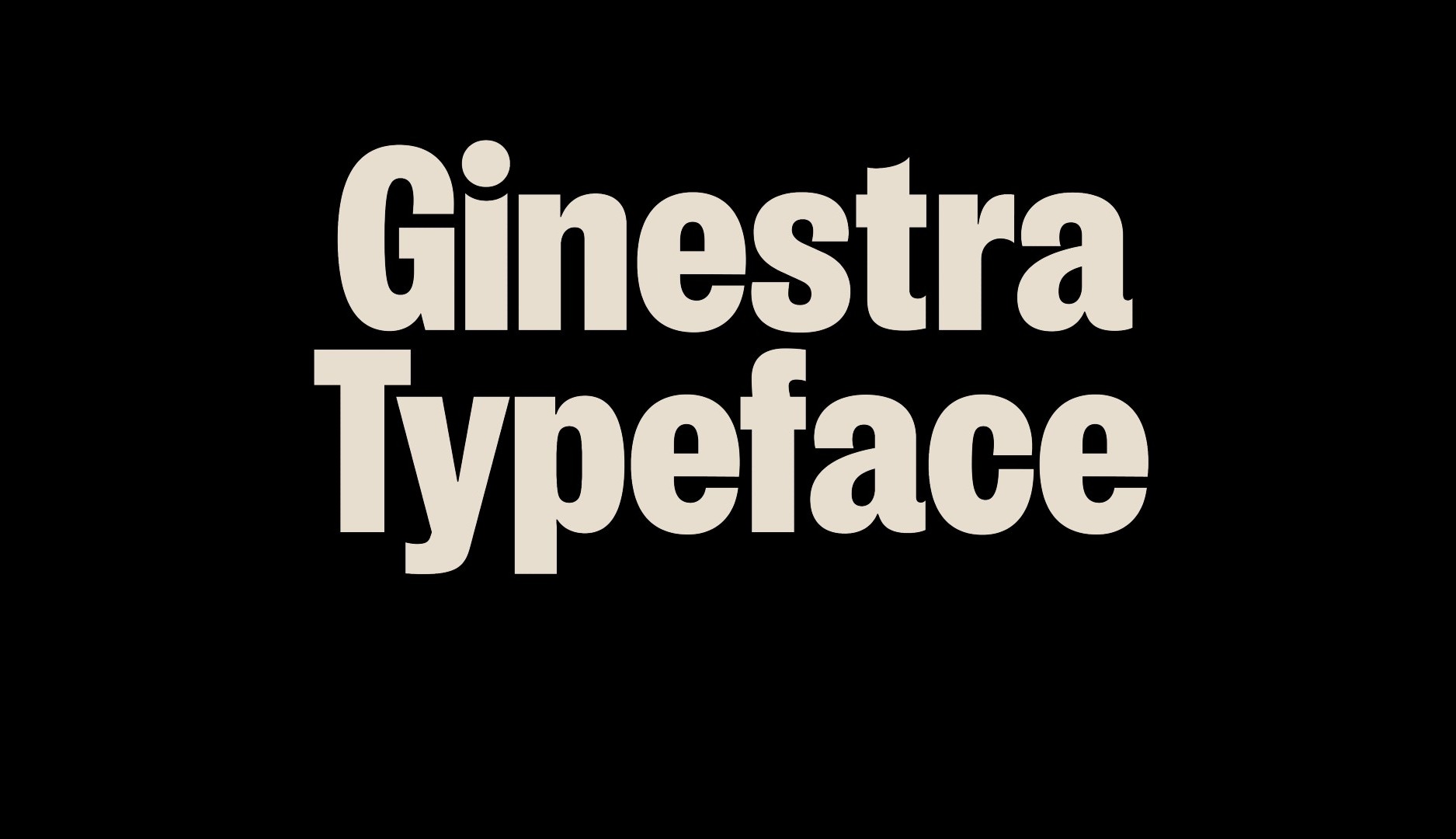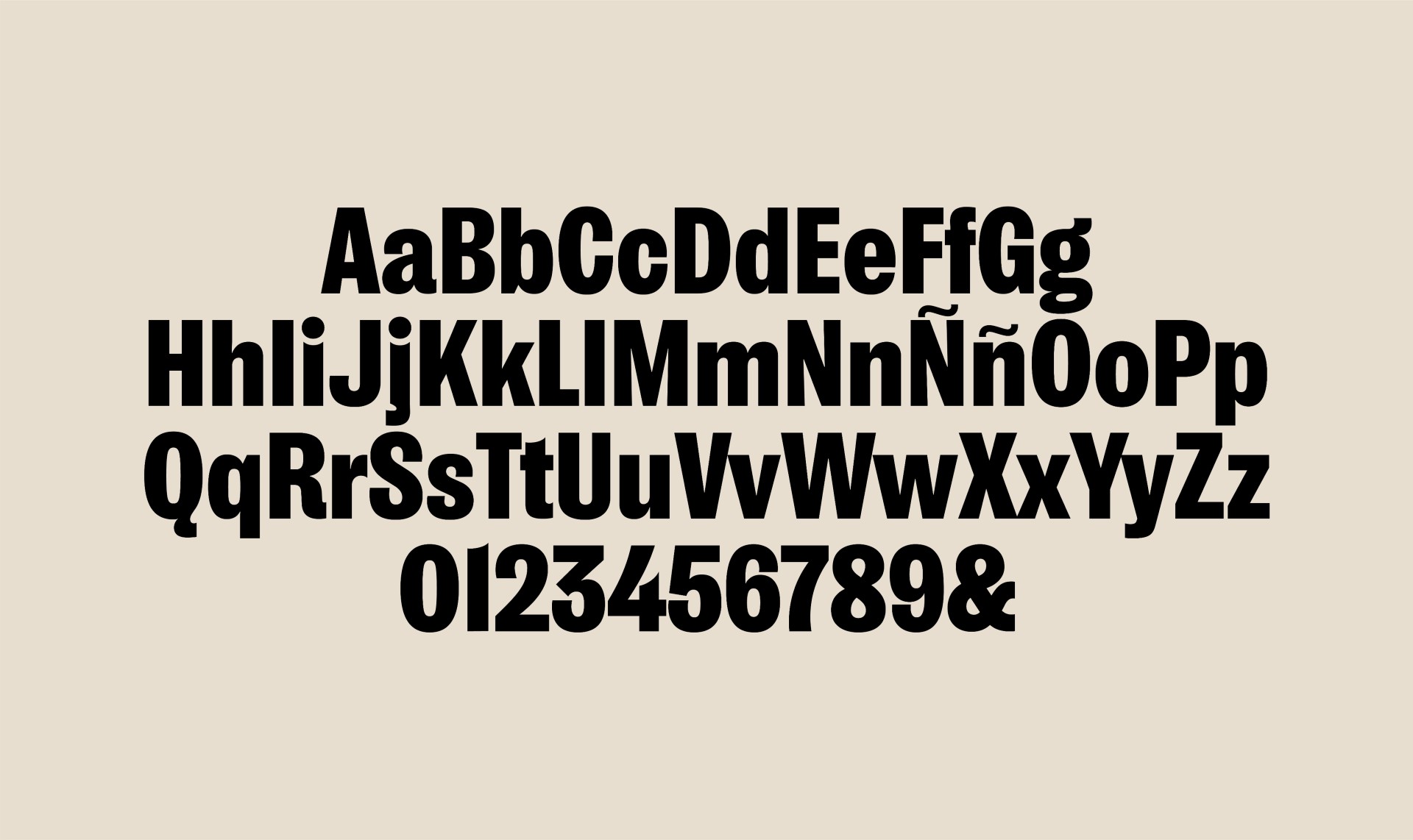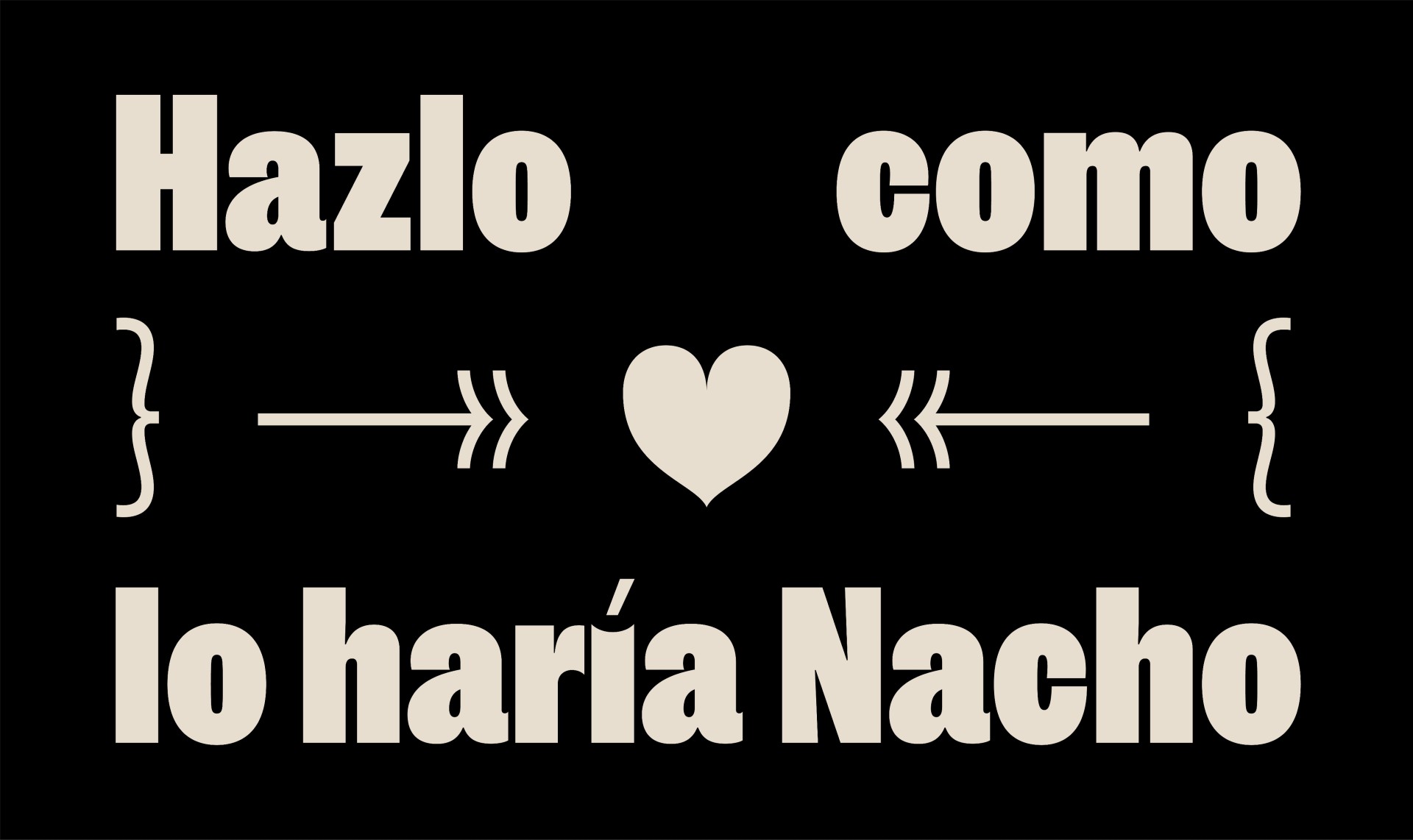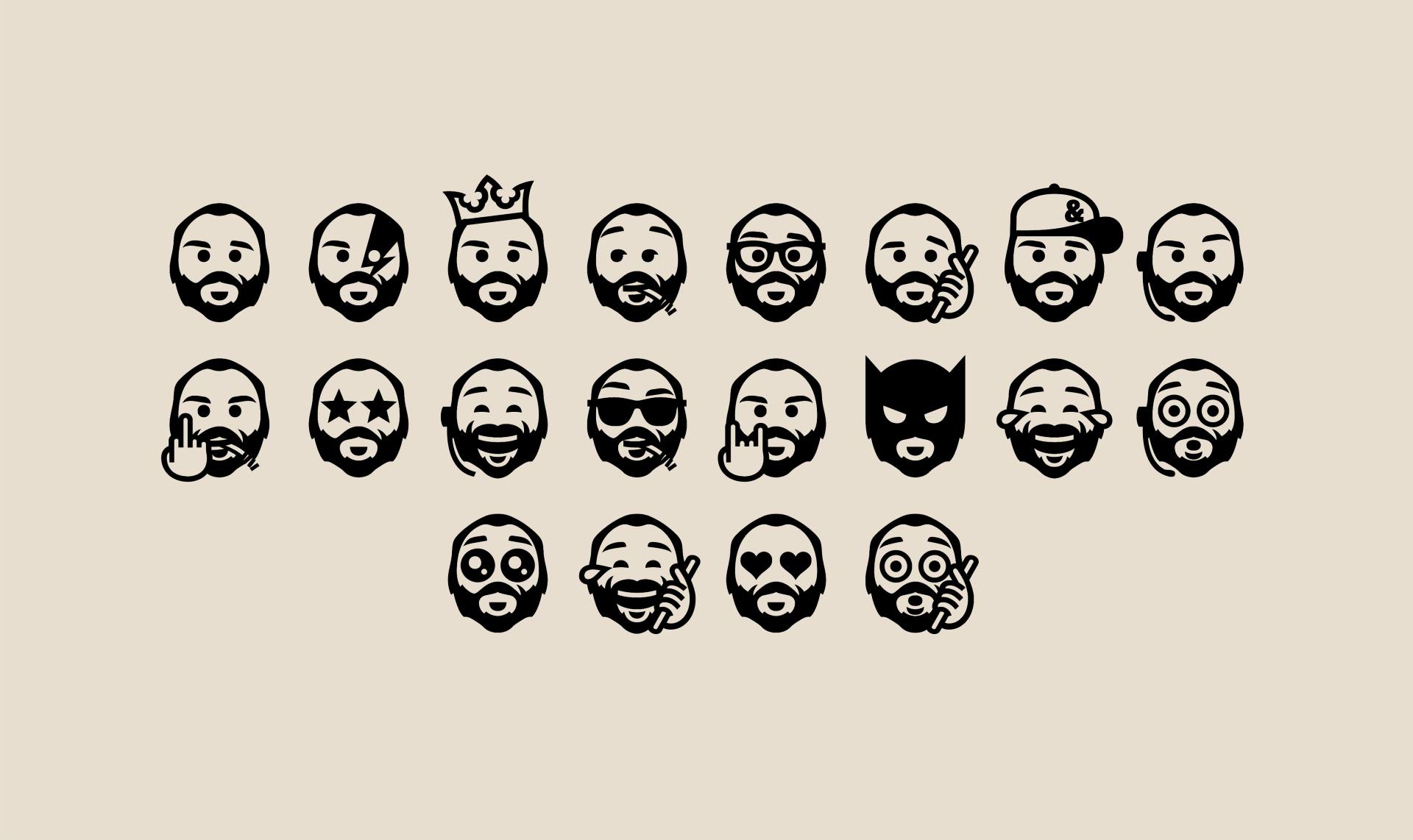
Tipografía “Ginestra”: la agencia &Rosás rinde homenaje al Director Creativo
• La agencia ha creado una tipografía inspirada en el creativo y tipografías propias del cartelismo
• Se ha diseñado en colaboración con Íñigo Jerez, Socio Fundador y Director Creativo de Extra Estudio
Tipografía Ginestra
Hace justo un año falleció Nacho Ginestra, quien fuera Director Creativo en &Rosàs, a consecuencia de una enfermedad. Con motivo del primer aniversario de su muerte y con la intención de rendirle un sentido homenaje, tanto a su persona como a su trayectoria profesional, la agencia ha creado una tipografía especial a la que ha concedido su nombre.
Nacho Ginestra colaboró anteriormente con el tipógrafo Íñigo Jeréz
Así, tipografía “Ginestra” ha sido ideada por &Rosás y diseñada junto a Íñigo Jerez, Socio Fundador y Director Creativo de Extra Estudio, junto a quien Nacho Ginestra, entre otras cosas, creó la tipografía “Creativa” para el Club de Creativos. La que ahora presenta la agencia está inspirada tanto en el Director Creativo como en la época del cartelismo, la predilecta del creativo.
Se trata de un momento, según nos explican los responsables de la agencia, en el que las tipografías cobraron especial protagonismo. Es más, la tipografía está inspirada en los primeros "palosecos" condensados del siglo XIX, cuando la tipografía salió del libro para protagonizar carteles de publicidad, y ya no se trataba solo de leer sino de comunicar.
“La tipografía refleja la personalidad de Nacho porque está llena de pequeños detalles, pero estos detalles son sutiles y están escondidos”, explica Isahac Oliver, Partner y Chief Creative Officer en &Rosàs, en declaraciones a Reason.Why. “Ahí se percibe la amabilidad, el buen humor, la diversión, pero también la contundencia”.
Desde la agencia señalan que el diseño de esta tipografía supone una forma de tener presente a Nacho Ginestra en todo lo que piensan y en todo lo que escriben. Es más, se convertirá en la tipografía oficial de la agencia y, por tanto, se usará en todas sus comunicaciones, tanto internas como externas, y se implementará también en el ampersand de su logotipo.
“La usaremos en todas nuestras presentaciones, en todos los e-mails que nos mandemos, en todas las ideas y en todos los conceptos que redactemos”, señalan desde la agencia. “Y, por supuesto, en el ampersand de nuestro logo, un ampersand que simboliza la unión de todos los que trabajan en &Rosàs”, explican, señalando que es la forma de tener presente a Nacho más allá de su memoria.
Pero &Rosàs no será la única que pueda disfrutar del legado del creativo, ya que la agencia ha habilitado una página web específica para que quienes lo deseen puedan descargar la tipografía de manera gratuita, aunque solo para usos personales y no comerciales. Consideran la iniciativa como “un regalo para todos los creativos y creativas” con el que aspiran a “embellecer el mundo en el que vivimos, algo que Nacho Ginestra hacía a diario con su trabajo”.
La tipografía se presenta en las variantes ultra, black, bold, semibold, medium y regular, y se muestras sus aplicaciones en diferentes grafismos. Además, la agencia acompaña la tipografía con una serie de pictogramas, concretamente 23, que ilustran el rostro de Nacho Ginestra en algunas sus caras y reacciones más características. “A Nacho le gustaba la idea de que una tipografía, además de caracteres, contase con pictogramas”, explican en la web. “Porque Nacho Ginestra no es solo un maestro y un grandísimo referente, también es un icono”.
El sitio web incluye experiencias y vivencias de profesionales que conocieron a Nacho
Además, en el sitio se recogen historias, anécdotas, experiencias y relatos de personas y profesionales que coincidieron con el creativo a lo largo de su vida y de su carrera profesional. Se podrán conocer los testimonios del creativo Toni Segarra; del director y guionista Julio Wallovits; de Jordi Rosàs, CEO de &Rosàs; o de Pipo Virgós, Director Creativo Ejecutivo en Wunderman Thompson. Todos ellos, y muchos más, dedican unas palabras a Ginestra y recuerdan lo que aprendieron de él.
“Este proyecto y la tipografía resultante nos sirve para poder tener a Nacho presente y que nos siga inspirando igual que hacía cuando estaba en la agencia”, nos comenta Isahac Oliver. “También es la oportunidad de hacer un homenaje a un gran creativo, que la gente conozca más sobre su figura y cómo nos ha marcado a nosotros, para que quienes no hayan tenido la oportunidad de conocerle puedan acercarse a él".